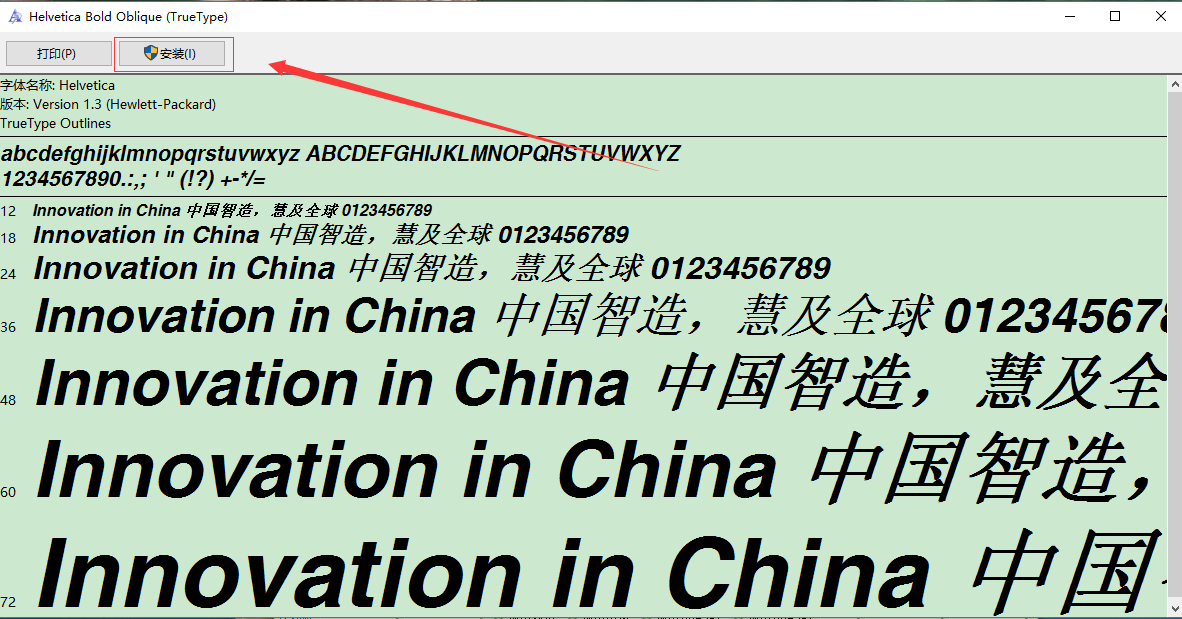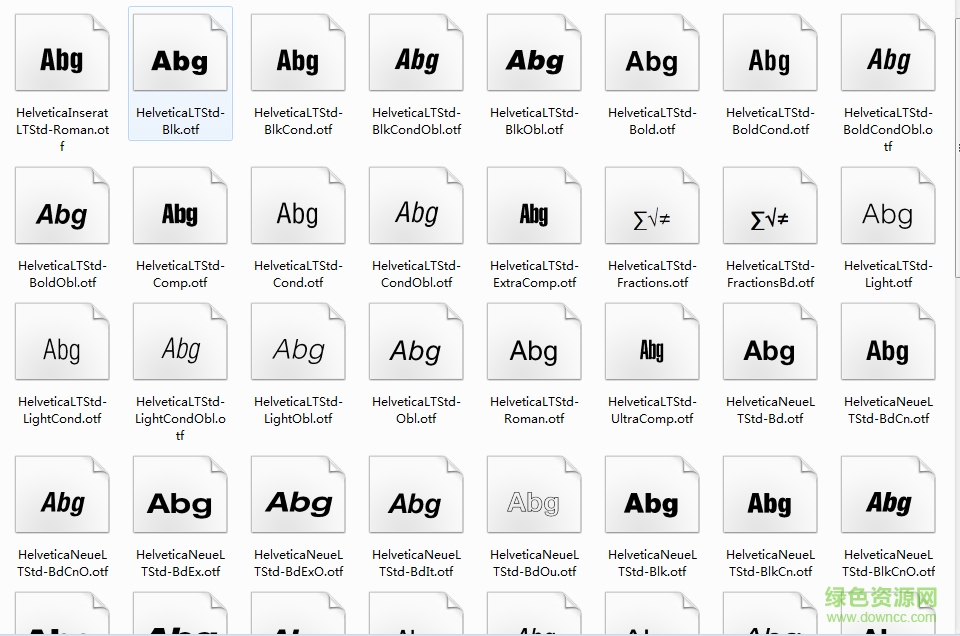
helvetica系列字體大全是廣受好評,并且使用非常廣泛的英文字體。helvetica字體家族包括了helvetica neue、helvetica light、helvetica now等多個系列,小編全部收集起來了,每款字體都極具個性風格迥異,使用簡單線條感十足,多款精品字體定能滿足您的需求。
helvetica字體是一款用于印刷行業(yè)設(shè)計字體,被評為設(shè)計師最愛的字體,Realist風格,簡潔現(xiàn)代的線條,非常受到追捧。字體體現(xiàn)了瑞士設(shè)計的理性主義精神,同時被認為是現(xiàn)代主義設(shè)計理念的典范。
1.在設(shè)計界的地位似乎無人能敵
2.已經(jīng)超過50年歷史的字體
3.擁有多種風格,多個版本
4.以獨特,專業(yè),永不過時而得到眾人的青睞
5.是世界上最受認可的字體